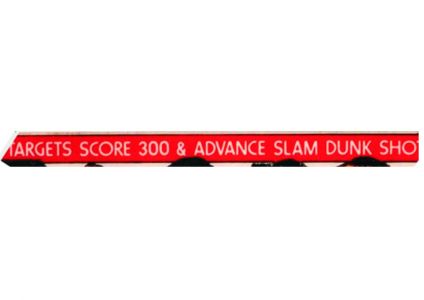
Wie heisst diese Schrift?
Für die Aufarbeitung eines ca. 30jährigen Flippers, suche ich die Schrift wie im Bild ersichtlich.
Sehr speziell bei der Schrift, ist das G und C.
Da ich die Schrift im Internet nicht finden konnte, hoffe ich im Forum, erkennt jemand diese Schrift.